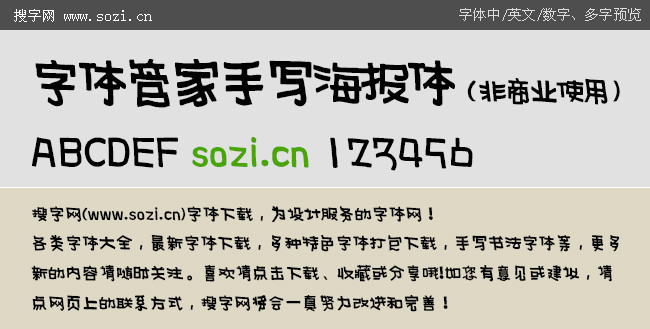
字體管家手寫海報(bào)體(非商業(yè)使用)
搜字網(wǎng)給大家提供一款字體管家手寫海報(bào)體(非商業(yè)使用)中文字體下載,該字體是一款個(gè)性的藝術(shù)字體,字體充滿變化,富有趣味。適合兒童包裝畫冊、書籍海報(bào)等廣告設(shè)計(jì)應(yīng)用(此字體為個(gè)人非商用版,商用可以聯(lián)系QQ:1006760504)。